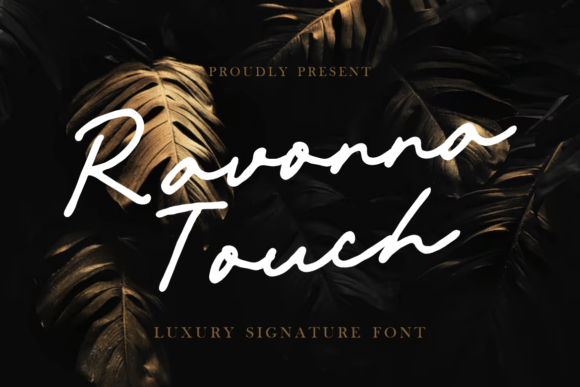
Ravonna Touch
Encontrar los elementos de diseño adecuados puede ser un desafío, pero Ravonna Touch ofrece una colección excepcional que eleva tu trabajo al instante.
Elaborado con precisión, Ravonna Touch proporciona vectores limpios, tipografía suave y una licencia comercial para tu tranquilidad.